Как проверить рукописные цифры в длинном номере без подсказок контекста
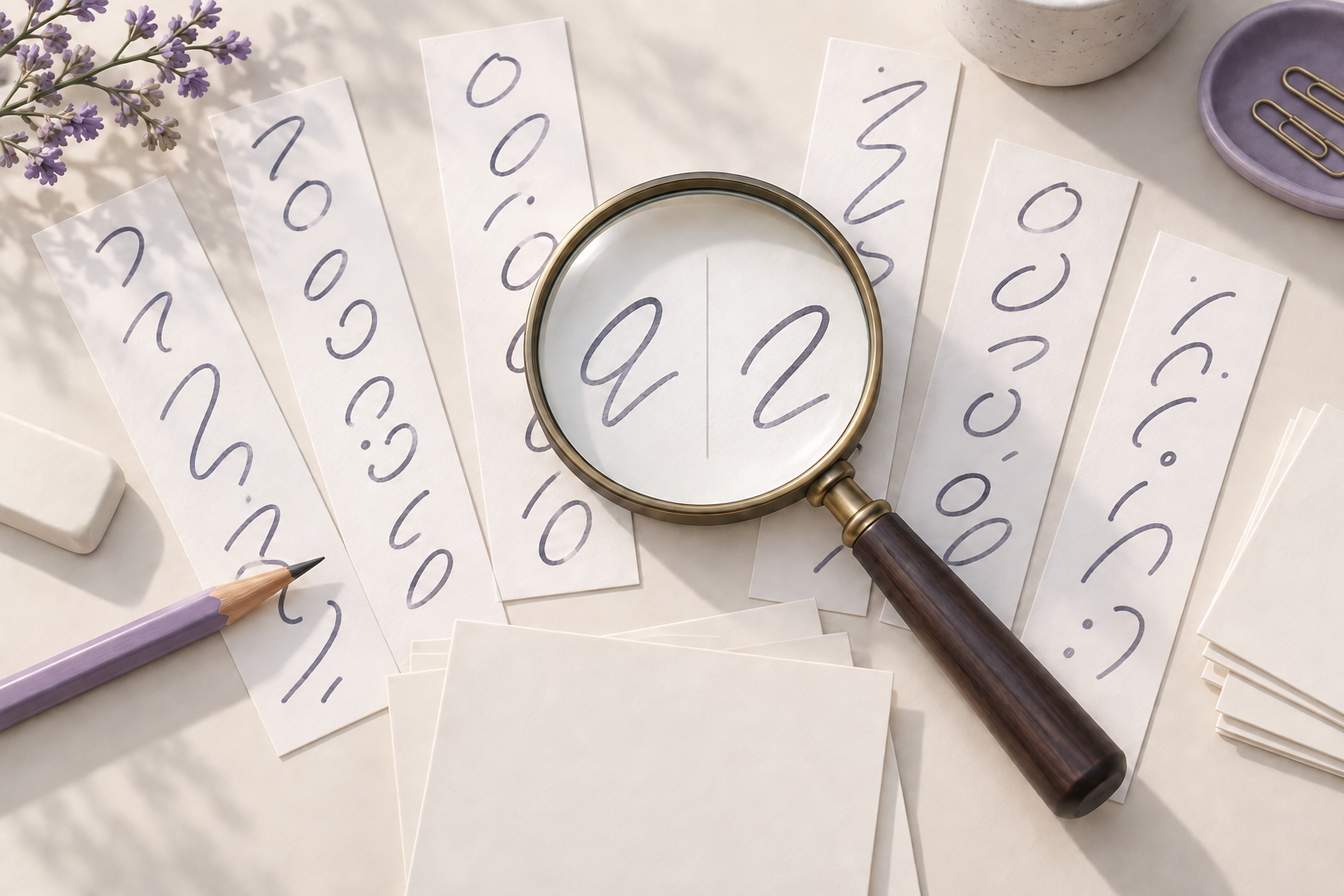
Рукописные цифры нужно проверять не только по отдельности: в длинном номере глаз читает цепочку, а не набор изолированных рисунков. Даже узнаваемая «3» может потеряться рядом с похожими формами, повториться так, что последовательность станет трудно сверять, или выглядеть двусмысленно при быстром чтении. Эта методика помогает оценить цифры в серийных номерах, кодах заказа и инвентарных записях до сборки шрифта: составить осмысленную пробу, провести чтение без подсказок, определить источник сбоя и править именно его.
Почему длинная последовательность выявляет слабые места
Проверка строки «0 1 2 3 4 5 6 7 8 9» полезна для обзора набора, но почти не похожа на чтение реального номера. Цифры в ней идут в ожидаемом порядке, каждая появляется один раз, а соседство заранее знакомо. В серийной записи встречаются повторы, резкие смены направлений штрихов, близкие контуры и длинные одинаковые фрагменты. Читатель уже не может опереться на счёт и пытается сверить каждую позицию с исходной записью.
Поэтому задача такой пробы — не выставить каждой цифре оценку за красоту. Нужно выяснить, можно ли правильно переписать последовательность, заметить пропущенный разряд и найти расхождение между двумя похожими номерами. Это отдельный сценарий: символы могут быть разборчивы в заголовке, но плохо работать в плотном числовом ряду.
Сначала задайте условия применения
Перед рисованием тестовых строк сформулируйте, где будут встречаться числа. Это запись от руки на бумаге, распечатанный текст, подпись на маленькой бирке или цифровая форма с моноширинным выравниванием? От ответа зависят размер пробы, фон, качество изображения и расстояние чтения. Для шрифта, которым заполняют карточки вручную, нужно проверять естественную скорость письма и соседство рукописных букв. Для готового файла шрифта важны ещё размер в макете, экспорт и то, как конкретная программа показывает цифры.
Опишите сценарий одной короткой фразой, например: «оператор сверяет номер партии с наклейкой» или «автор переносит инвентарный код из журнала в таблицу». Выберите одну задачу для этой пробы. Если смешать этикетку, экран и заполнение от руки, будет трудно понять, откуда возникла ошибка: из формы цифры, размера, контраста или процесса переписывания.
Соберите тестовые строки, а не случайный набор
Возьмите несколько настоящих по структуре примеров из своей задачи, но замените личные и коммерческие значения вымышленными. Сохраните длину, дефисы или другие разделители и характер повторов. Затем добавьте контрольные последовательности, в которых каждая цифра встречается в начале, середине и конце, а самые похожие формы оказываются рядом. Важно менять только одну особенность за раз: иначе непонятно, что именно показала проба.
Подготовьте три группы. Первая — равномерная: цифры встречаются по одной в обычном порядке. Вторая — с повтором: одна форма повторена два или три раза рядом, затем чередуется с другой. Третья — с потенциально трудным соседством и сменой ритма: например, плавные замкнутые формы рядом с узкими прямыми. Это не готовый универсальный список ошибок, а способ увидеть рисунок вашего набора. Запишите исходные строки отдельно, чтобы позже сверить копию посимвольно.
Проверьте не только одиночные цифры, но и пары
Разложите набор на пары соседних цифр. В некоторых шрифтах проблема проявляется не в одной форме, а в стыке: у одного символа остаётся длинный входной штрих, у другого — такой же выход; два узких силуэта сливаются; округлая цифра подходит слишком близко к следующей. Составьте несколько строк, где одна и та же пара повторяется в разных местах, и сравните интервалы рядом с другими парами.
Проверяйте пары в обе стороны. Связка «2–7» может читаться иначе, чем «7–2», если у цифры асимметричный вход или наклон. Не стремитесь сделать все промежутки одинаковыми по линейке. Ищите равномерный визуальный ритм при сохранении разницы между формами. Если пользователь должен читать номер по ячейкам, границы разрядов можно дополнительно показать сеткой в макете; сам шрифт не обязан изображать каждую цифру отдельной кнопкой.
Три режима проверки: узнавание, копирование и сверка
Первый режим — узнавание: покажите строку на короткое время и попросите прочитать её вслух. Запишите, какую цифру участник назвал в каждом месте, а не только итоговую ошибку. Второй режим — копирование: дайте исходную запись и попросите переписать номер в другом поле. Сравните оригинал и копию позиция за позицией. Третий режим — сверка: покажите рядом два почти одинаковых номера и попросите найти отличие.
Эти проверки отвечают на разные вопросы. Узнавание показывает, насколько быстро символы складываются в последовательность. Копирование выявляет пропуски и повторный счёт. Сверка обнаруживает формы, которые различаются лишь при внимательном сравнении. Не подсказывайте ответ и не проговаривайте сложное место заранее: задача — увидеть самостоятельную реакцию. После каждого прохода спросите, где участник задержался, но не объясняйте причину до записи результата.